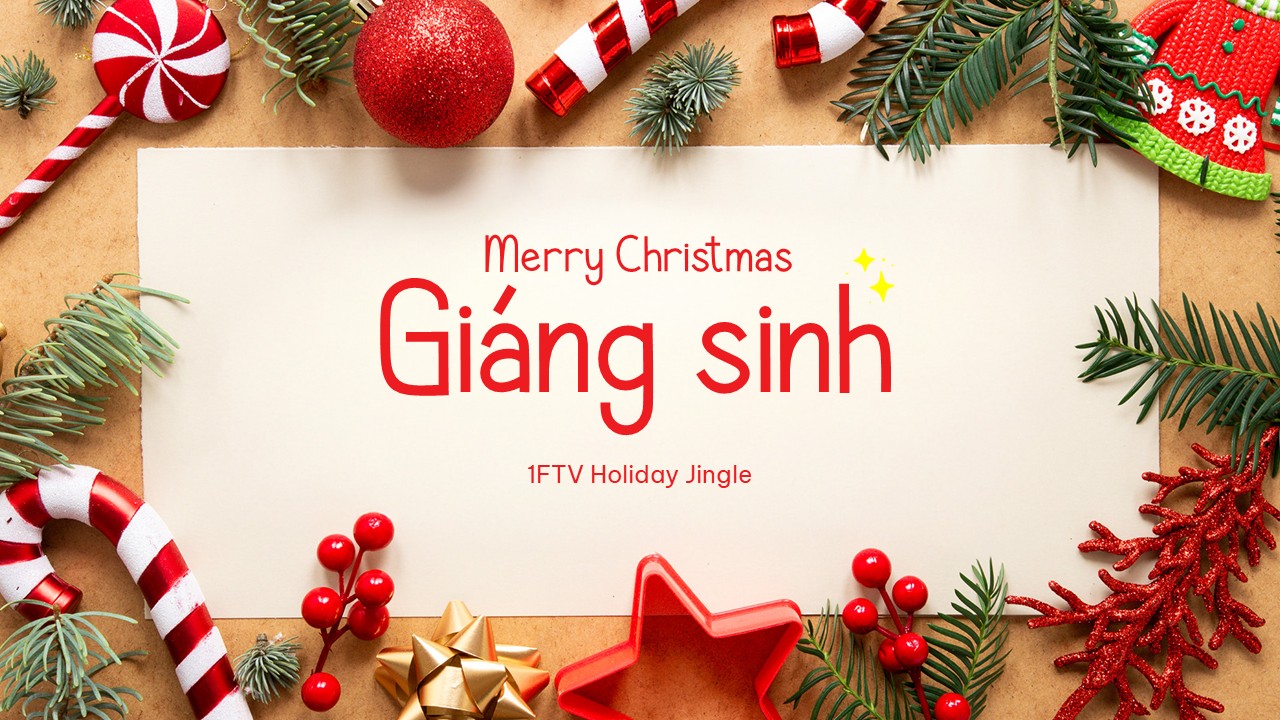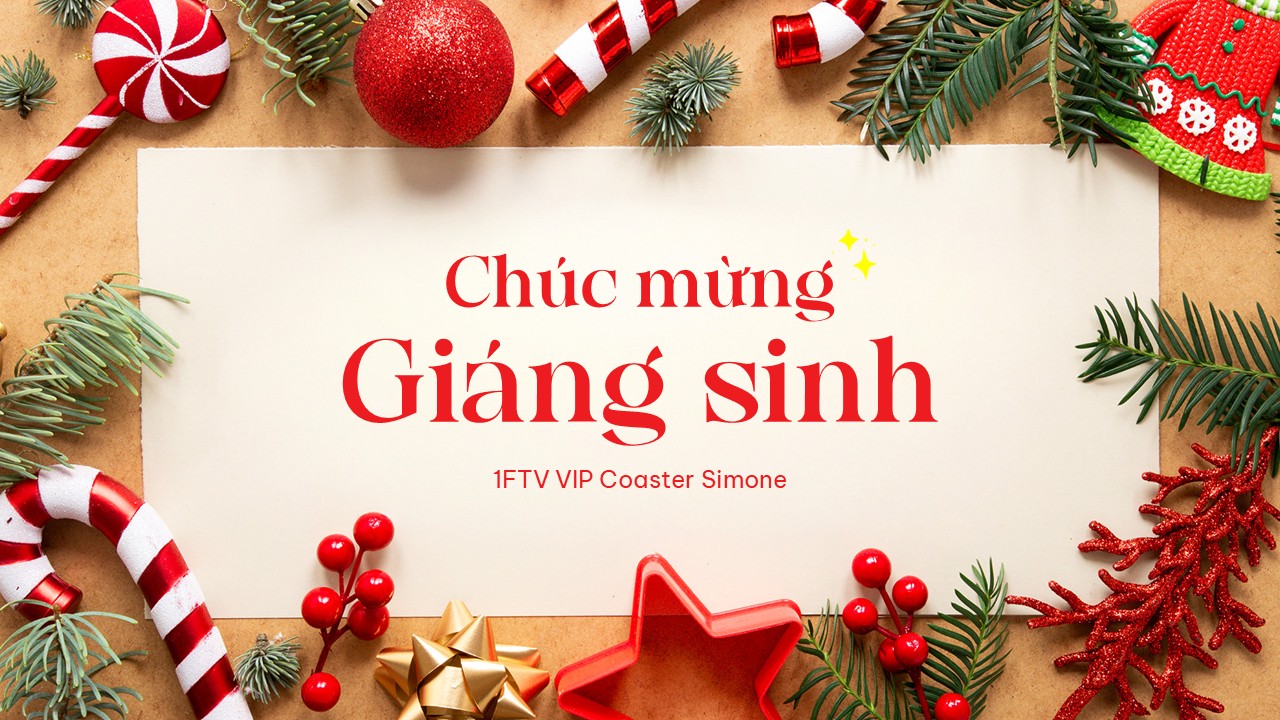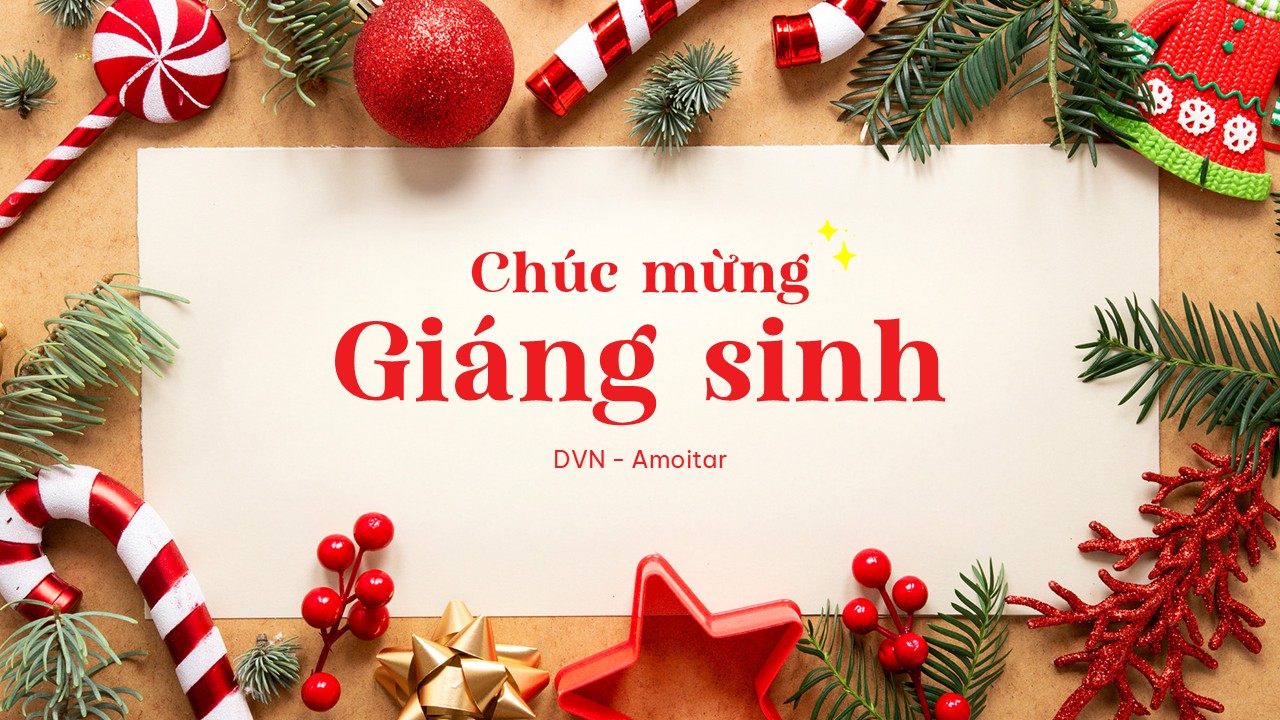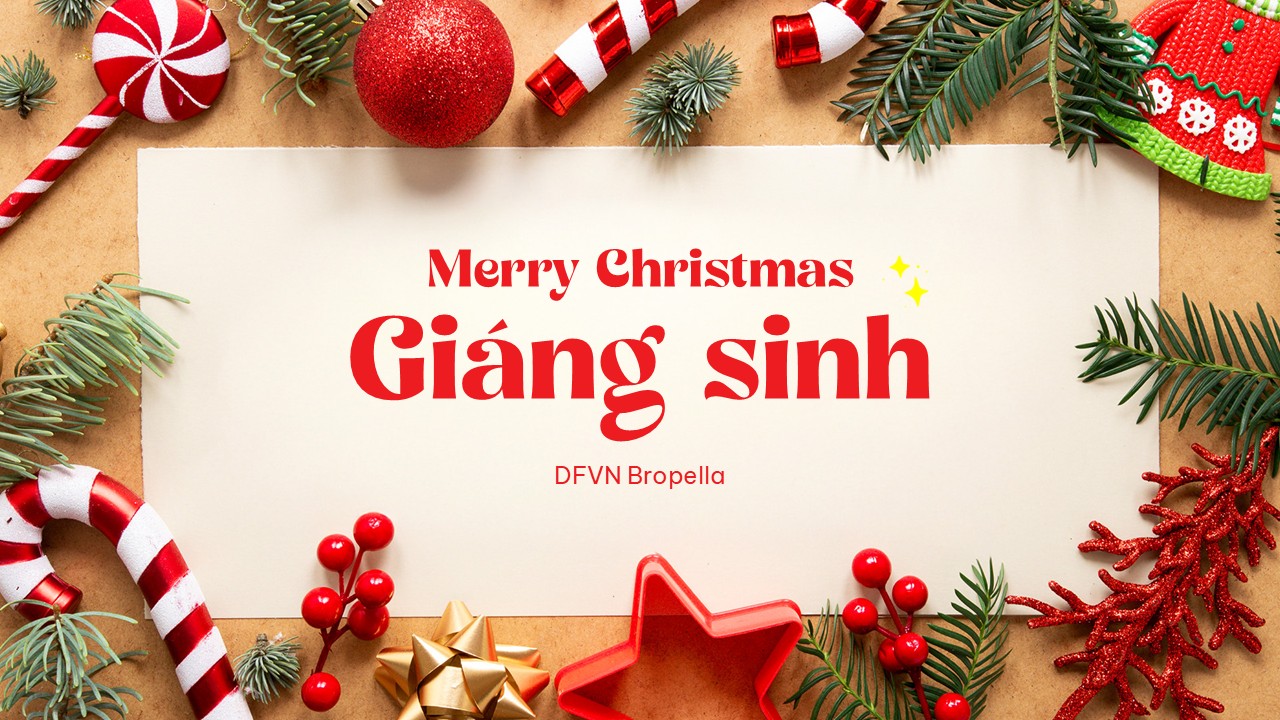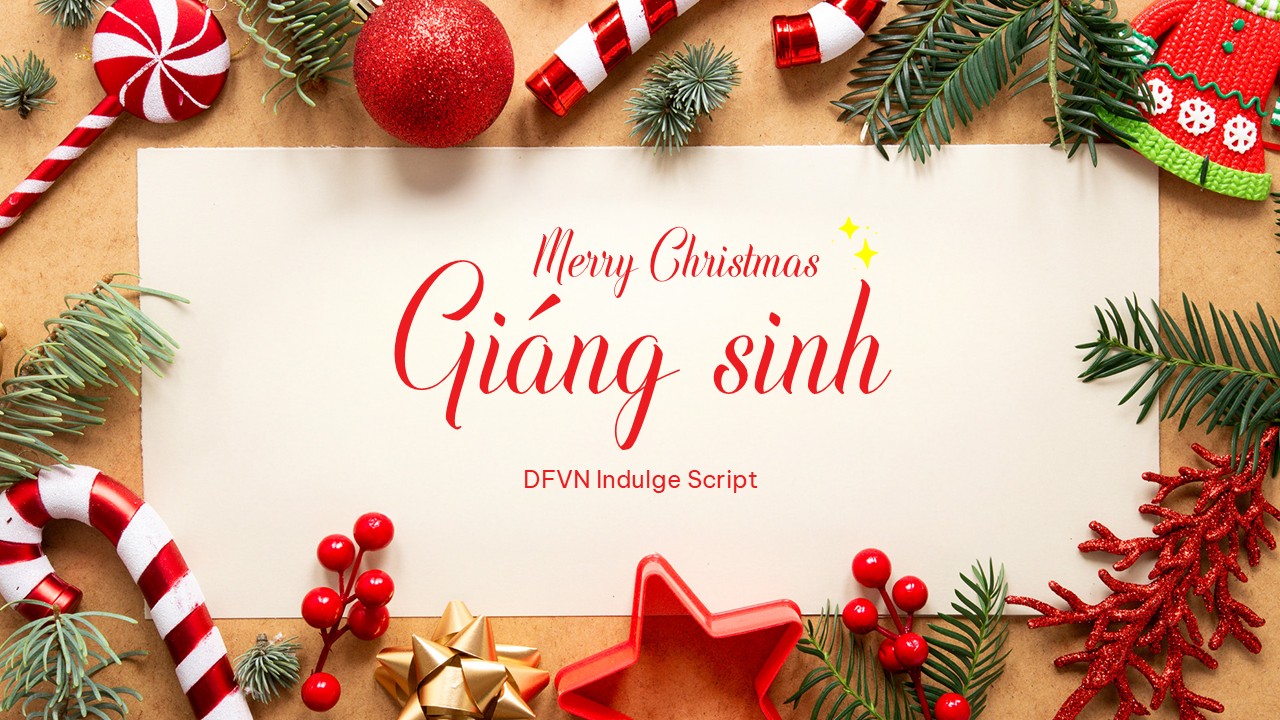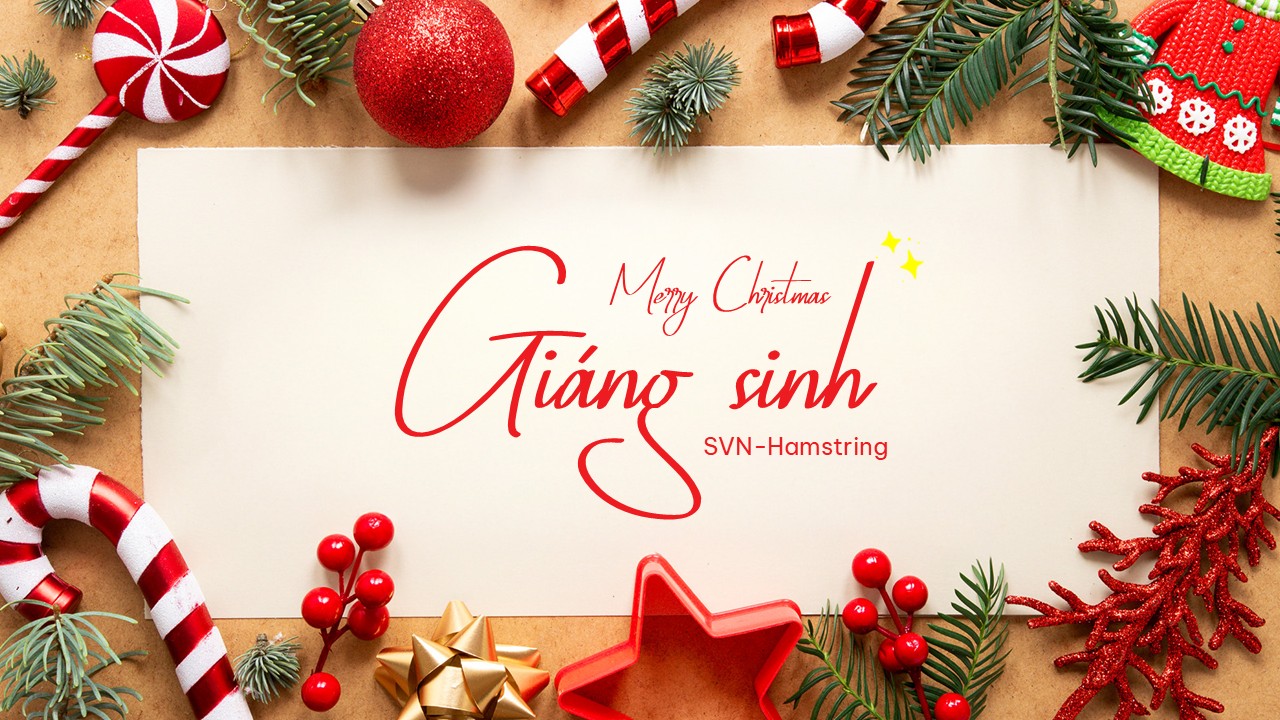
Top 8 Font Chữ Giáng Sinh Việt Hóa Đẹp Lung Linh Cho PowerPoint & Thiết Kế Noel 2025
Bạn đang đau đầu tìm font chữ Giáng sinh đẹp, hỗ trợ tiếng Việt đầy đủ để làm mẫu slide PowerPoint Giáng sinh, mẫu thiệp Giáng sinh hay mẫu social post Giáng sinh mà không bị lỗi dấu? Mình từng như vậy suốt mấy mùa Noel, dùng font ngoại quốc xinh nhưng viết “Chúc Mừng Giáng Sinh” là… méo mó hết cả!
May sao năm nay 2025, mình đã “khám phá” ra top 8 font chữ Giáng sinh Việt hóa miễn phí siêu đỉnh, festive lung linh, dùng ngay trong PowerPoint mà không lo lỗi font. Đảm bảo đọc xong bạn sẽ thốt lên: “Trời ơi sao giờ mới biết mấy font này!!!”
1. Tại sao 99% bạn trẻ dùng font Giáng sinh đều bị lỗi dấu tiếng Việt?
Đúng không nào? Bạn tải font Noel đẹp từ Dafont hay Google Fonts về, apply vào mẫu slide PowerPoint Giáng sinh thì… “Giáng Sinh” thành “Giang Sinh” mất dấu, hoặc chữ xấu xí kinh khủng!
Lý do đơn giản: Hầu hết font Giáng sinh quốc tế không hỗ trợ đầy đủ Unicode tiếng Việt. Kết quả? Mẫu thiệp Giáng sinh gửi crush bị “lộ” nghiệp dư, mẫu social post Giáng sinh lên feed nhìn chán òm. Mình từng mất hàng giờ fix, giờ thì không nữa nhờ font Việt hóa!
2. Top 8 font chữ Giáng sinh Việt hóa đẹp nhất 2025 (miễn phí tải ngay)
Mình chọn lọc kỹ chỉ những font festive, hỗ trợ dấu tiếng Việt đỉnh cao, dùng lý tưởng cho mẫu slide thiết kế Giáng sinh và mẫu PowerPoint Noel. Tải về cài vào là dùng ngay!
1FTV Holiday Jingle – Vui nhộn như chuông Noel, siêu hợp tiêu đề lớn. Tải miễn phí: Click đây
1FTV VIP Coaster Simone – Script sang chảnh, romantic cho lời chúc. Tải miễn phí: Click đây
Amoitar Regular – Serif tinh tế, chuyên nghiệp cho slide thuyết trình. Tải miễn phí: Click đây
Bropella – Handwritten nhiều glyph, aesthetic Gen Z mê. Tải miễn phí: Click đây
Indulge Script – Handwritten ấm áp, flow mượt như bút lông. Tải miễn phí: Click đây
Kingsguard Calligraphy – Calligraphy cổ điển, fairy tale vibe. Tải miễn phí: Click đây
Machinery Script – Script mạnh mẽ, modern cá tính. Tải miễn phí: Click đây
- SVN-Hamstring – Casual trẻ trung, everyday Noel. Tải miễn phí: Click đây
4. Các lỗi thường gặp khi dùng font Giáng sinh & fix trong 3 giây
2. Font nào đẹp nhất cho mẫu thiệp Giáng sinh handwritten?
Coaster Simone hoặc Indulge Script – romantic max level!
Với top 8 font chữ Giáng sinh Việt hóa này, bạn sẽ làm mẫu slide PowerPoint Giáng sinh, mẫu thiệp Giáng sinh hay mẫu social post Giáng sinh đẹp lung linh chỉ trong vài phút. Thử ngay đi, đảm bảo Noel 2025 “slay” hết nấc!